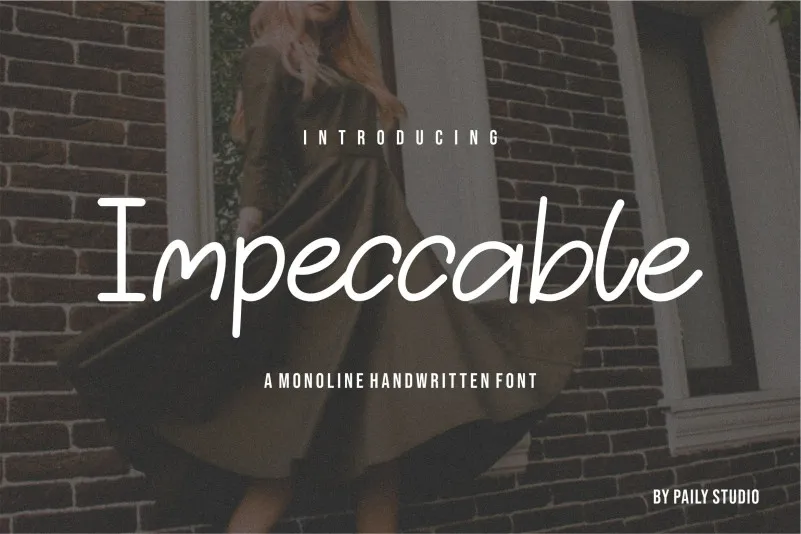
Impeccable Font – Fonte Grátis
Impeccable Font
A Impeccable Font é uma escolha perfeita para designers buscando uma tipografia elegante e duradoura que pode ser usada em um vasto conjunto de projetos. Perfeita para aplicações como casamentos, identidades corporativas, logomarcas, postais, cartões de visita e até mesmo posts nas redes sociais, a Impeccable se destaca pela sua legibilidade e estabilidade, mantendo sempre seu estilo sofisticado. Seu design curvilíneo e harmonioso combina perfeitamente com um range vasto de projetos, tornando-a uma fonte de eleição para qualquer projeto que exija elegância e profissionalismo. Com a Impeccable, você pode adicionar um toque de sofisticação ao seu próximo trabalho de design.
Designer: Paily Studio